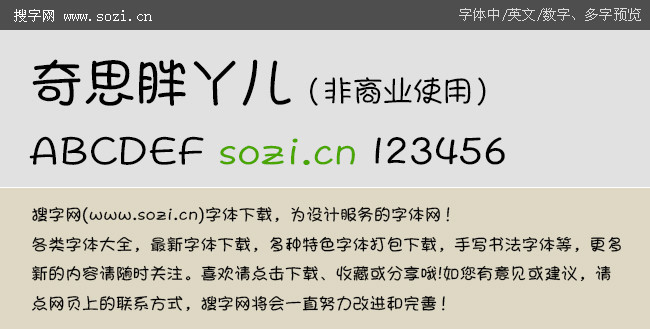
奇思胖丫兒(非商業(yè)使用)
搜字網(wǎng)給大家提供奇思胖丫兒(非商業(yè)使用)中文藝術(shù)字體下載,這是一款卡通字體,字體俏皮可愛,充滿趣味性,適合卡通畫冊、海報設(shè)計等廣告設(shè)計使用(此字體為個人非商用版,如需商用請聯(lián)系作者購買版權(quán))。